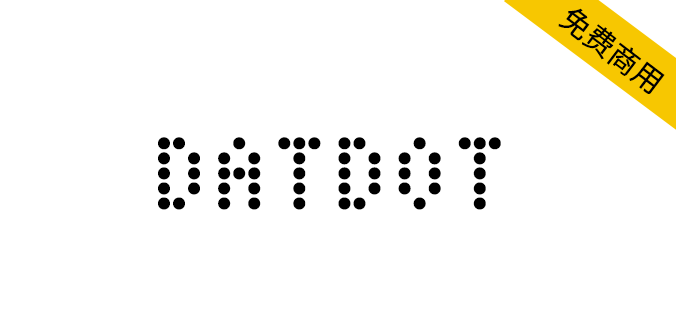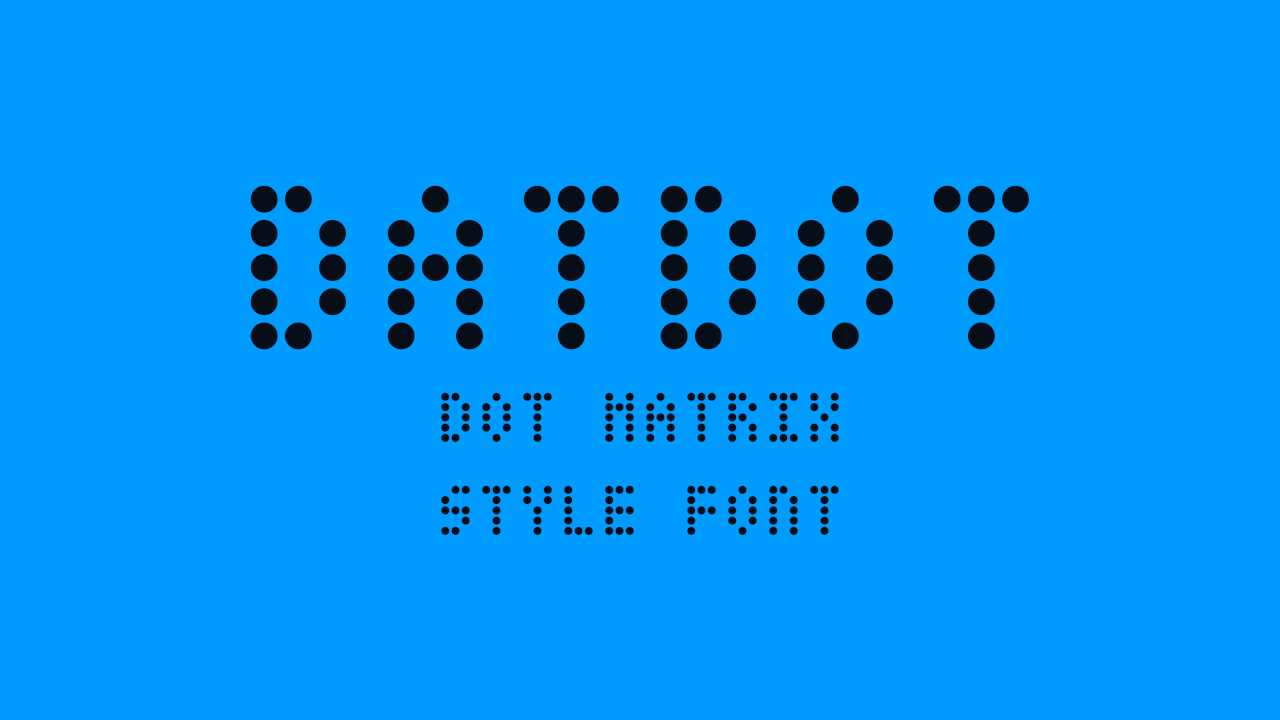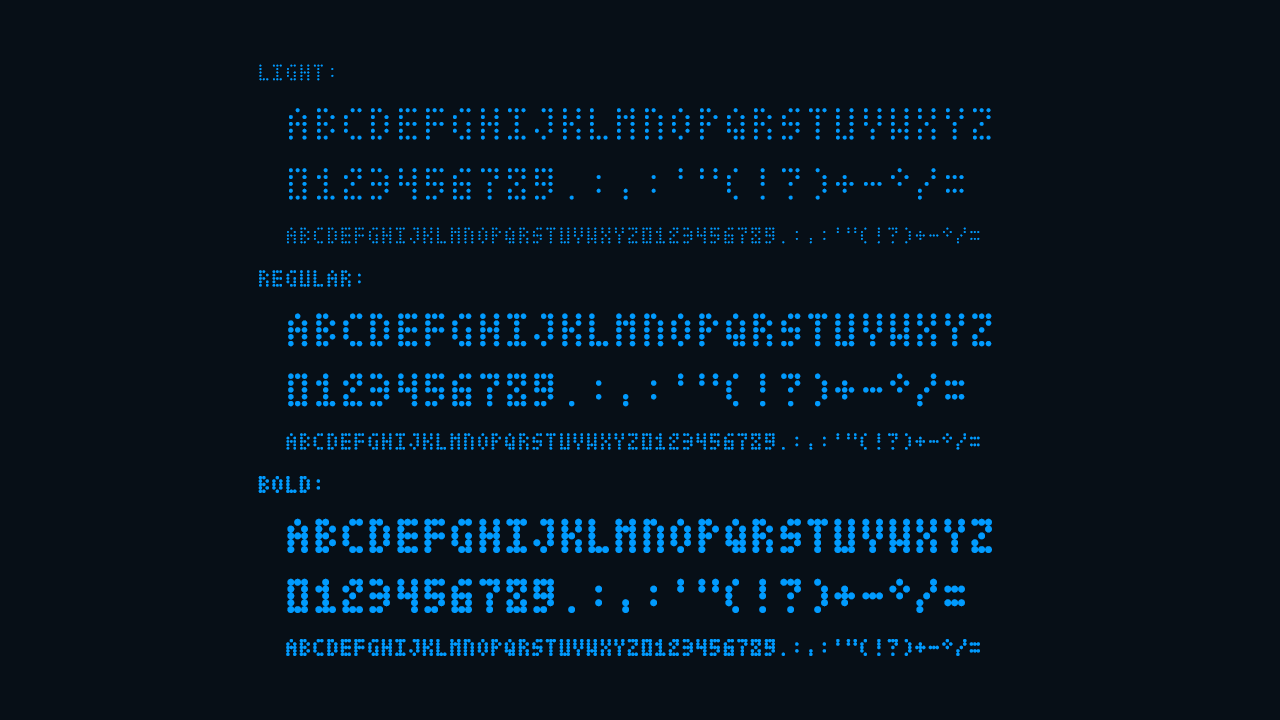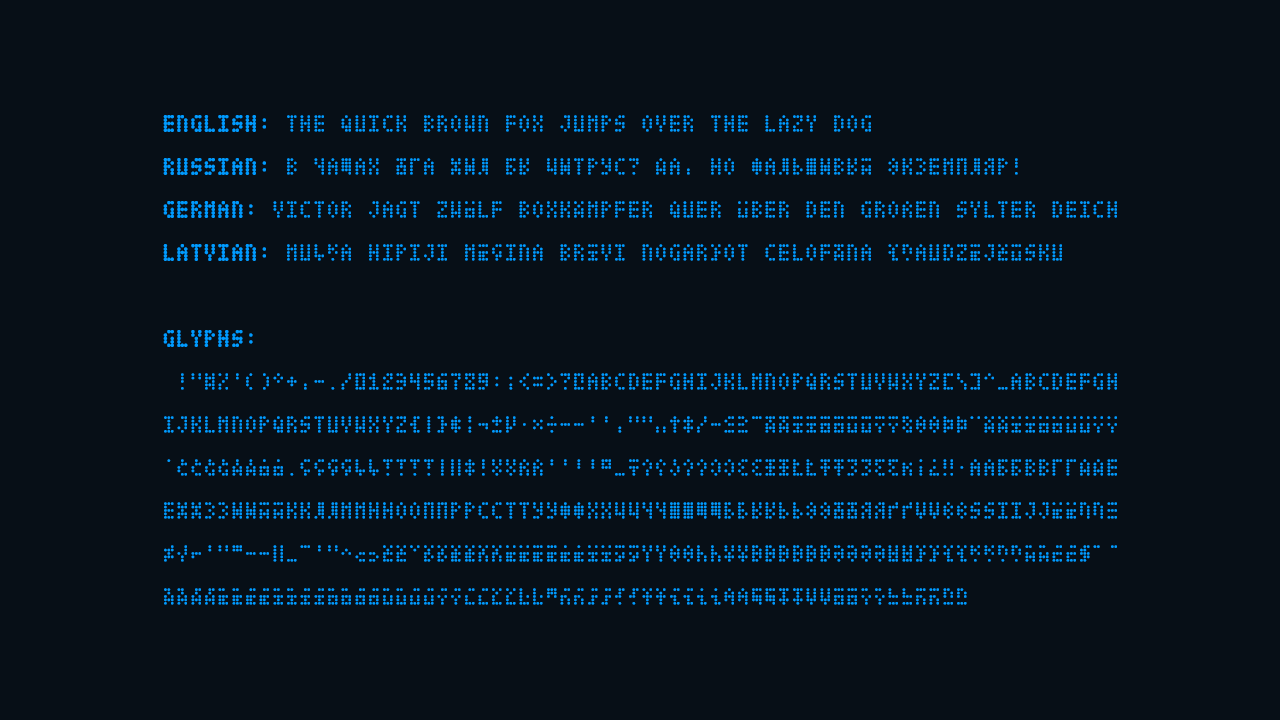
DatDot是一款圆形点阵样式英文字体,根据SIL OFL协议发布, 有3种样式(Regular、Bold、Light)和 410个字形。
布局网格 3x5(固定宽度和高度)。
支持 33 种语言(Aja, 阿尔巴尼亚语, 白俄罗斯语, 保加利亚语, 加泰罗尼亚语, 克罗地亚语, 达格巴尼语, 荷兰语, 英语, 爱沙尼亚语, Fon, 德语, 印度尼西亚语, 意大利语, 拉丁语, 拉脱维亚语, 立陶宛语, 马赛语, Mapudungun, 蒙古语, 北萨米语, 波兰语, 俄语, 苏格兰盖尔语,塞尔维亚语、斯洛文尼亚语、西班牙语、他加禄语、特拉帕内克语、乌克兰语、乌兹别克语、西弗里斯兰语、祖鲁语。)